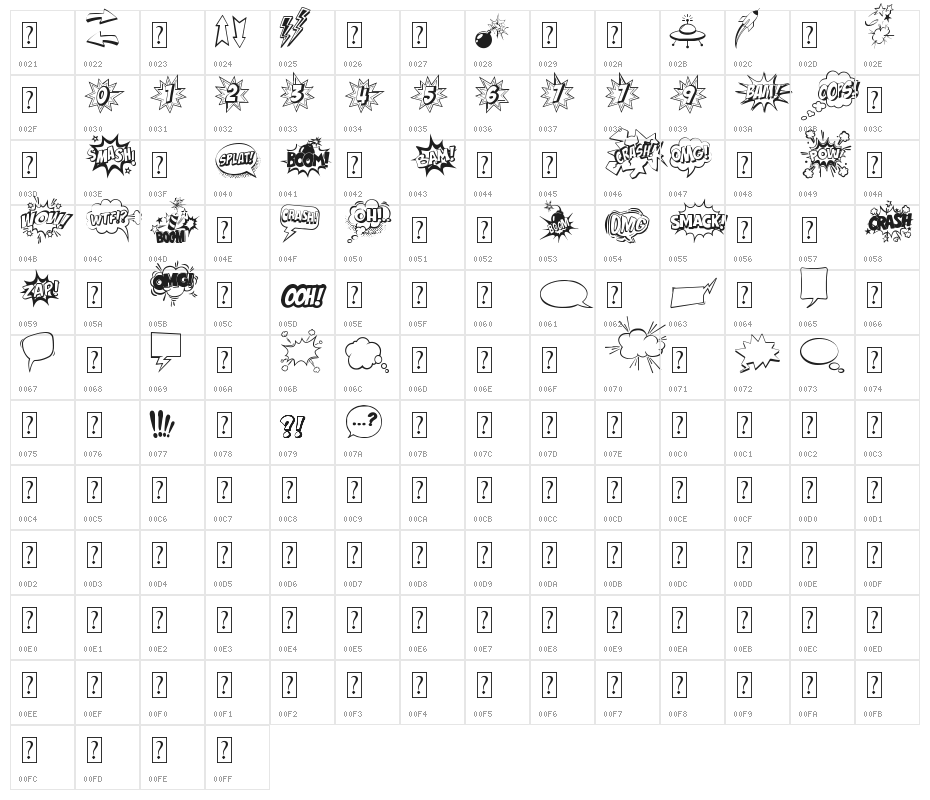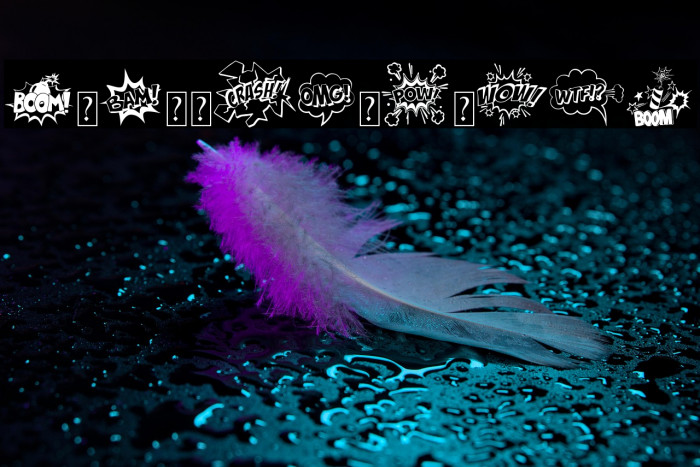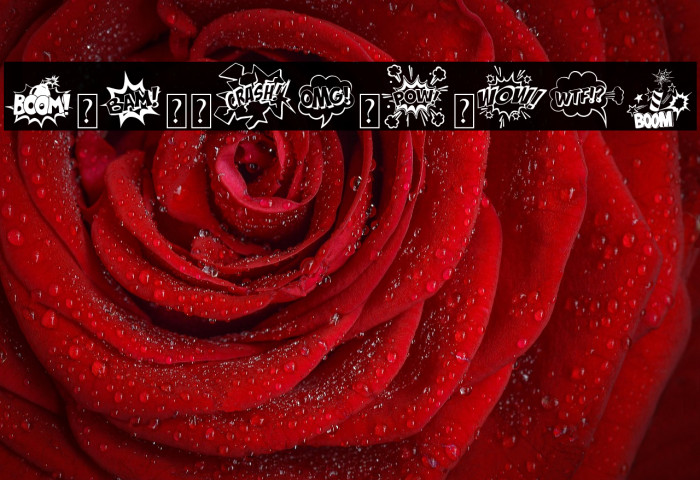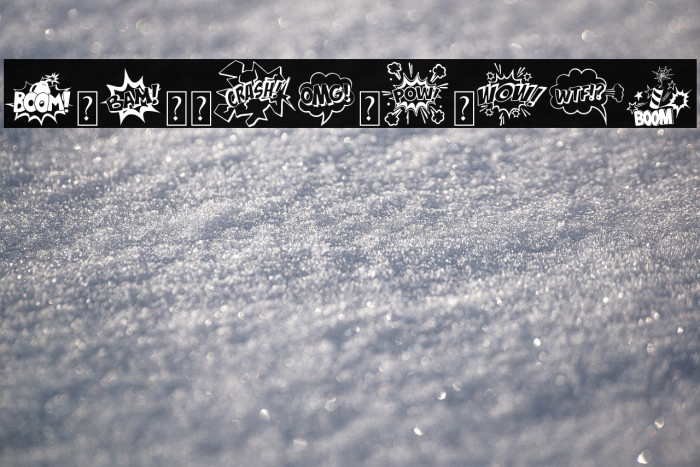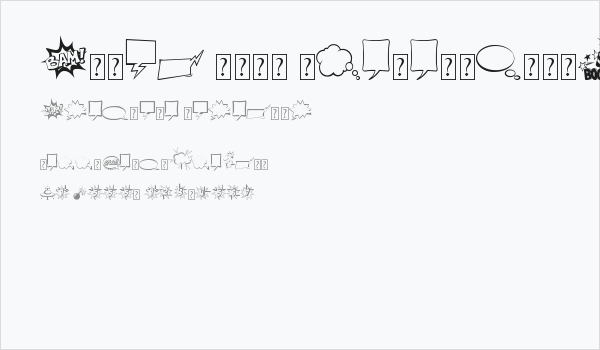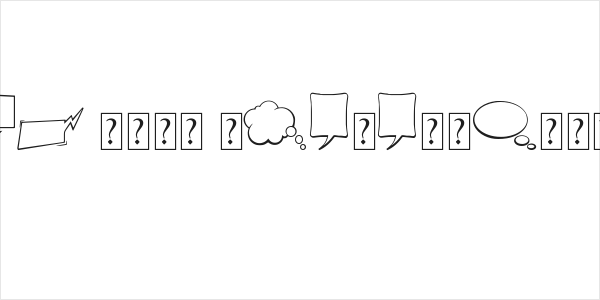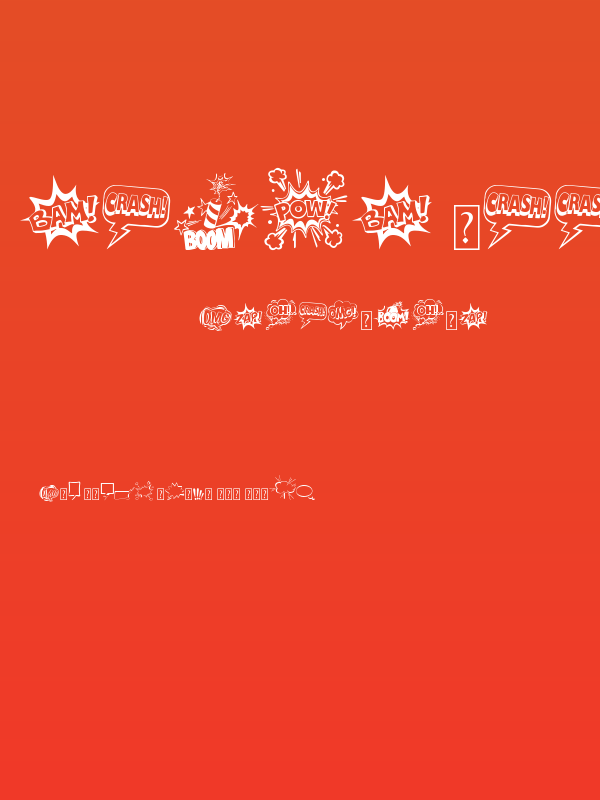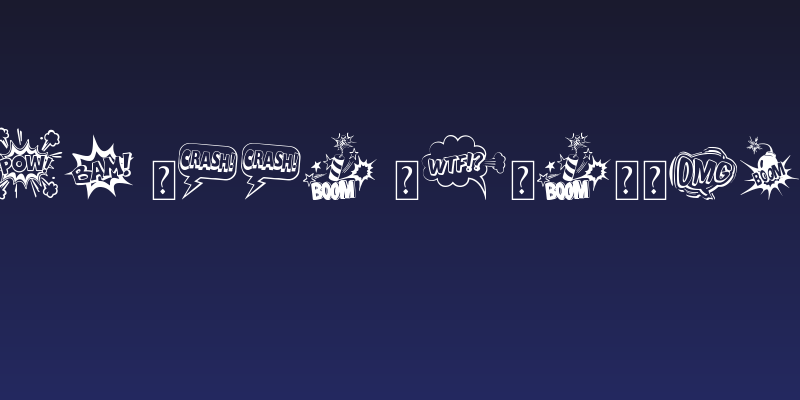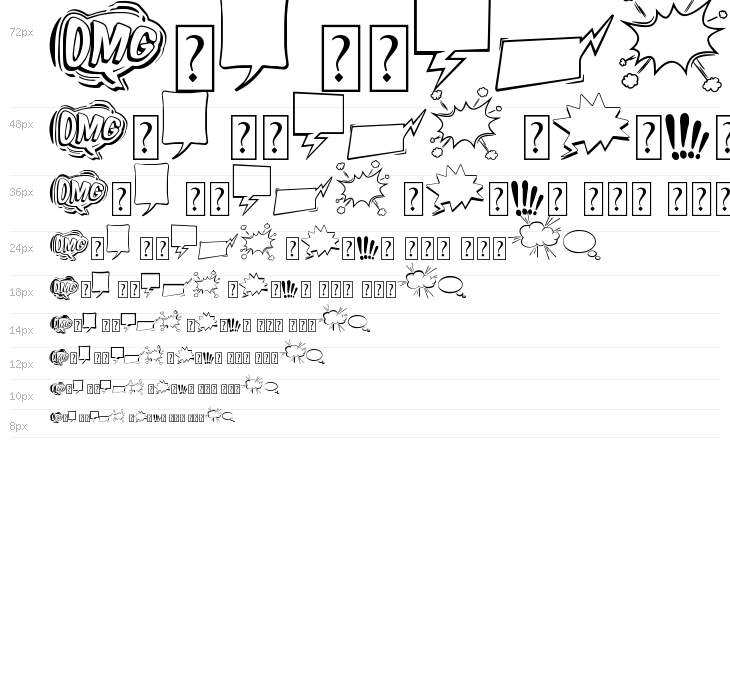
Comic Boom Elements_DEMO Font
| Stile generale | Playful, Energetic, Comic |
| Caso d'uso | Logos, Posters, Comic Books |
| Progetti proposti | Ideal for comic book designs, children's book illustrations, playful posters, and dynamic advertisements. |